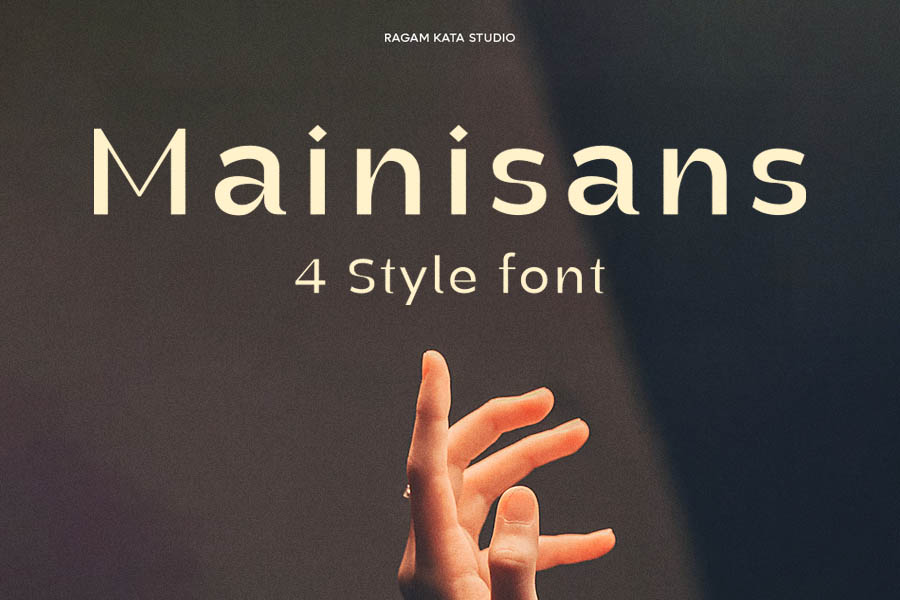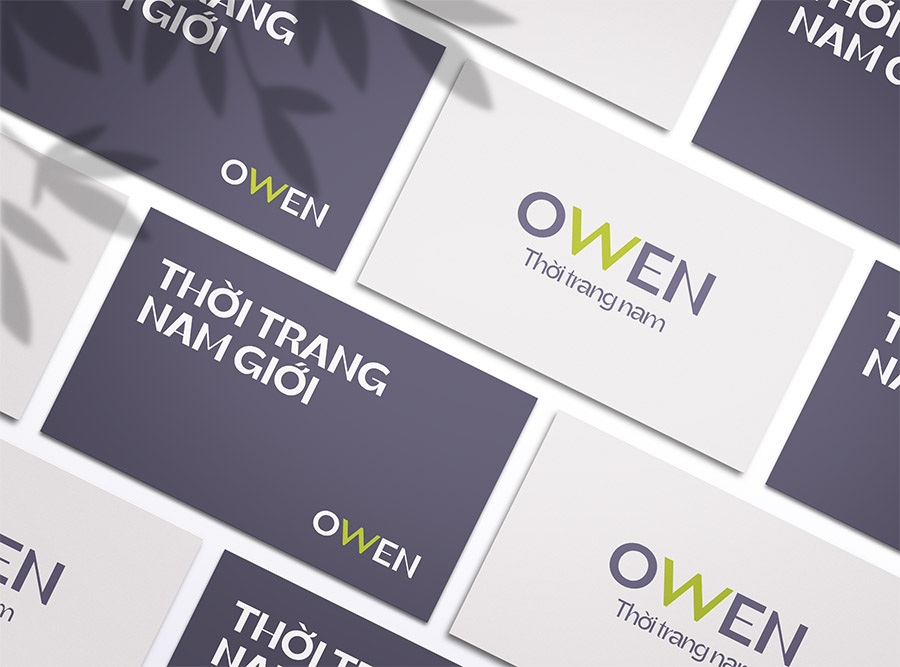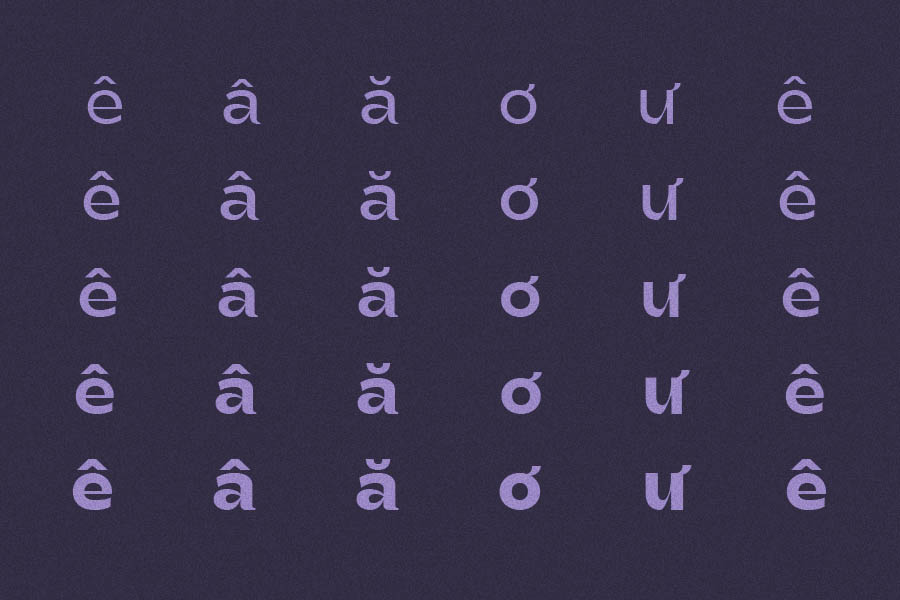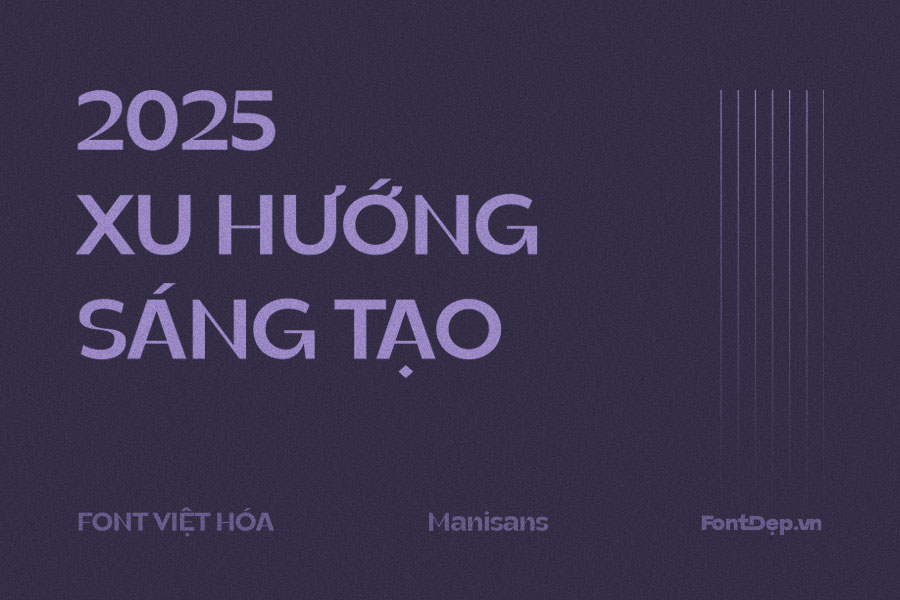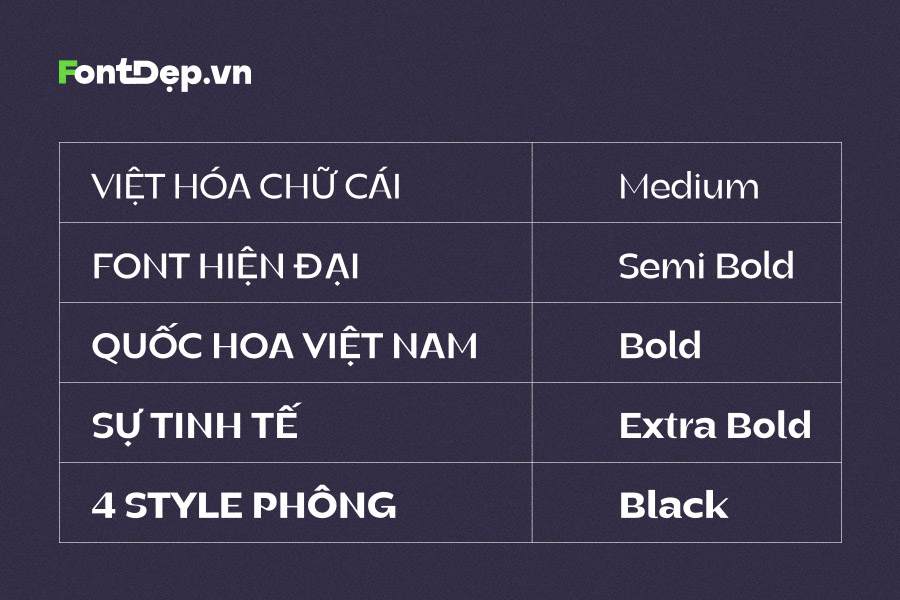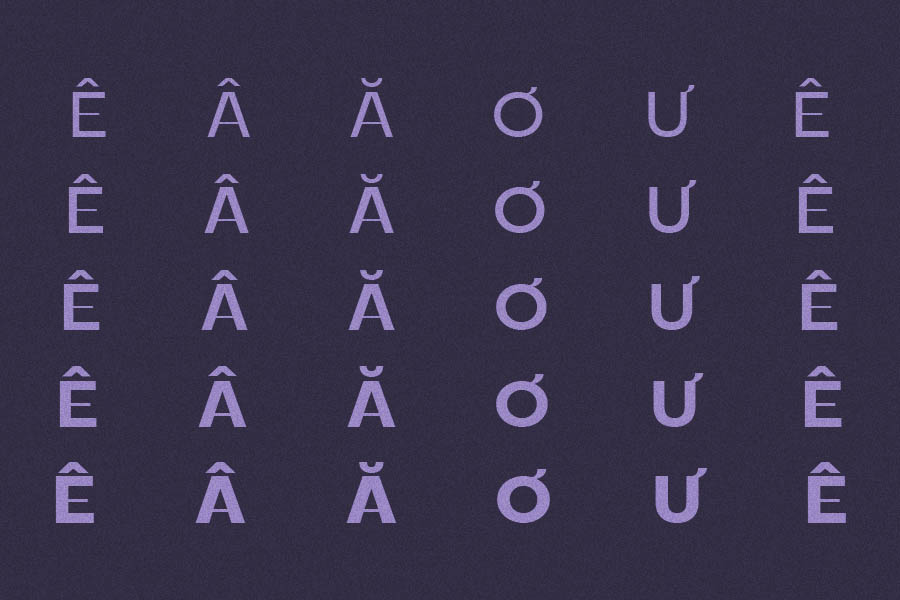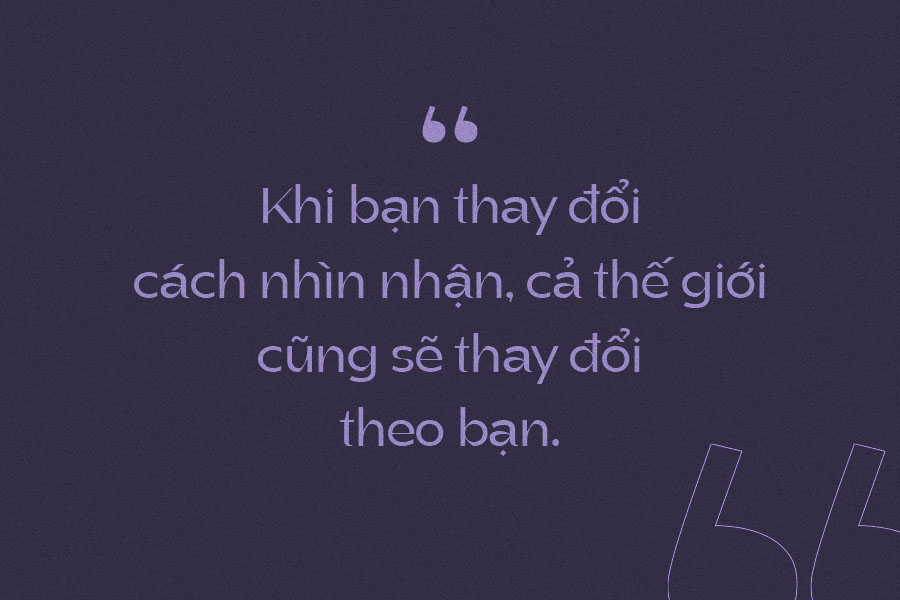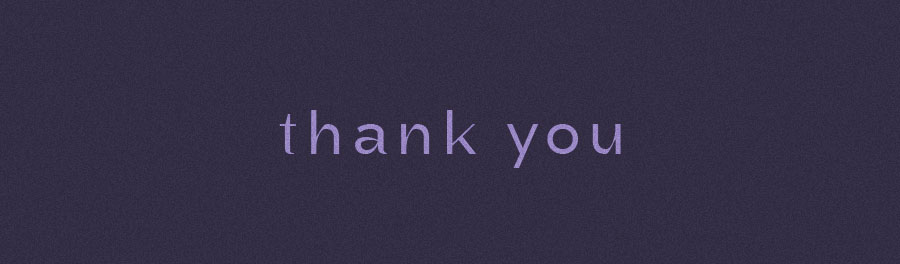
Font Chữ TH Manisans Việt hóa Hiện Đại và Sang Trọng
Tác giả Måns Grebäck
Trong thế giới thiết kế hiện đại, một font chữ sans-serif không chỉ cần đẹp mắt mà còn phải thể hiện được sự linh hoạt, sang trọng và chuyên nghiệp trong từng chi tiết. Bộ font TH Manisans chính là đại diện tiêu biểu cho xu hướng đó. Với thiết kế thanh lịch và tinh giản, font chữ này không chỉ đáp ứng tốt nhu cầu thẩm mỹ mà còn hỗ trợ đầy đủ tiếng Việt – đặc biệt phù hợp cho thiết kế thương hiệu, truyền thông và giao diện số.
Giới Thiệu Chung Về Font TH Manisans
TH Manisans là phiên bản Việt hóa hoàn chỉnh từ bộ font Manisans gốc của nhà thiết kế nổi tiếng người Thụy Điển – Måns Grebäck. Được biết đến với hàng trăm bộ font script và sans-serif nổi tiếng trên toàn cầu, Måns Grebäck luôn tạo ra các bộ font có tính ứng dụng cao, dễ dùng và mang cá tính riêng biệt. Phiên bản TH Manisans được Việt hóa bởi Phạm Sơn, người đứng sau dự án Fontdep.vn, đảm bảo hiển thị chuẩn tiếng Việt mà không bị lỗi dấu, lệch dấu như nhiều font quốc tế khác.
Điểm đặc biệt của TH Manisans là bộ font này có 5 style đã được Việt hóa đầy đủ, bao gồm:
• TH Manisans Medium
• TH Manisans SemiBold
• TH Manisans Bold
• TH Manisans ExtraBold
• TH Manisans Black
Mỗi style mang cá tính riêng, từ nhẹ nhàng tinh tế đến cực kỳ mạnh mẽ – tạo điều kiện tối đa cho việc ứng dụng linh hoạt trong nhiều hoàn cảnh thiết kế khác nhau.
Thiết Kế Và Phong Cách Của TH Manisans
Font TH Manisans thuộc nhóm sans-serif hiện đại, với các đường nét gọn gàng, sắc nét và cân đối. Kiểu chữ được thiết kế với tỷ lệ hài hòa, tạo cảm giác dễ đọc ở mọi kích thước, đồng thời vẫn giữ được tính thẩm mỹ cao.
Một số đặc điểm nổi bật:
Không chân hiện đại: Loại bỏ hoàn toàn các chi tiết chân chữ, giúp kiểu dáng chữ sạch sẽ, tinh gọn và thân thiện với thiết kế kỹ thuật số.
Trọng số đậm dần hợp lý: Từ Medium đến Black, mỗi style đều có sự điều chỉnh tinh tế ở độ dày nét, giúp nhà thiết kế chọn được đúng "tone chữ" cho từng nội dung.
Cân bằng tốt giữa hình khối và khoảng cách: Điều này giúp font không bị “bí” ở size nhỏ và vẫn đủ mạnh mẽ ở size lớn.
Việt Hóa Chỉn Chu – Hỗ Trợ Đầy Đủ Tiếng Việt
Phiên bản Việt hóa được thực hiện tỉ mỉ, không lỗi dấu, không vỡ nét khi in ấn hay hiển thị trên màn hình. Dù bạn thiết kế bằng Photoshop, Illustrator, hay dùng trên Canva, PowerPoint – TH Manisans đều hiển thị mượt mà, ổn định. Việc hỗ trợ đầy đủ Unicode tiếng Việt giúp bạn yên tâm dùng cho mọi nội dung: từ slogan thương hiệu cho đến các đoạn nội dung dài.
Tổng Kết
Bộ font TH Manisans không chỉ là một font sans-serif đẹp mắt, mà còn mang tính ứng dụng cực cao nhờ thiết kế chỉnh chu, hiện đại và hỗ trợ tiếng Việt hoàn hảo. Với 4 style Medium, SemiBold, Bold, ExtraBold đã Việt hóa, đây là lựa chọn lý tưởng cho mọi designer đang tìm kiếm một bộ font mạnh mẽ, sang trọng và dễ sử dụng trong năm 2025.